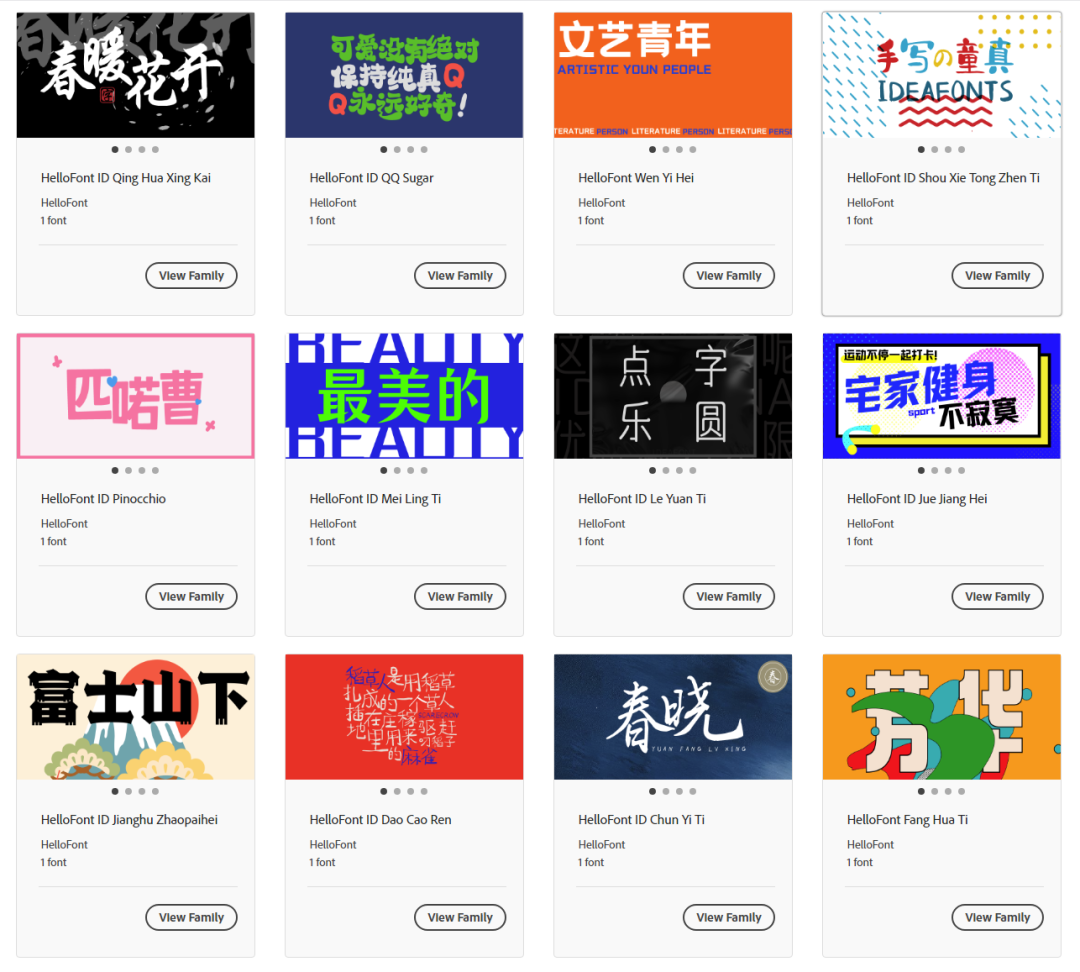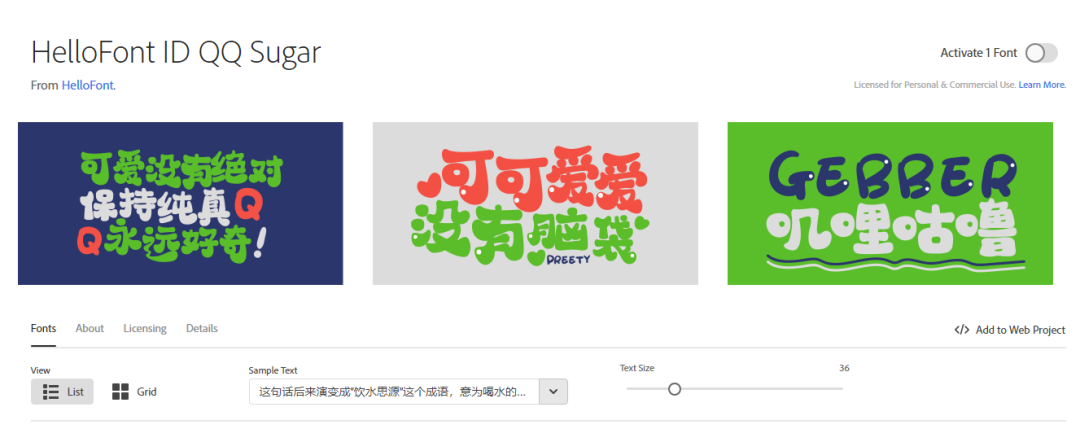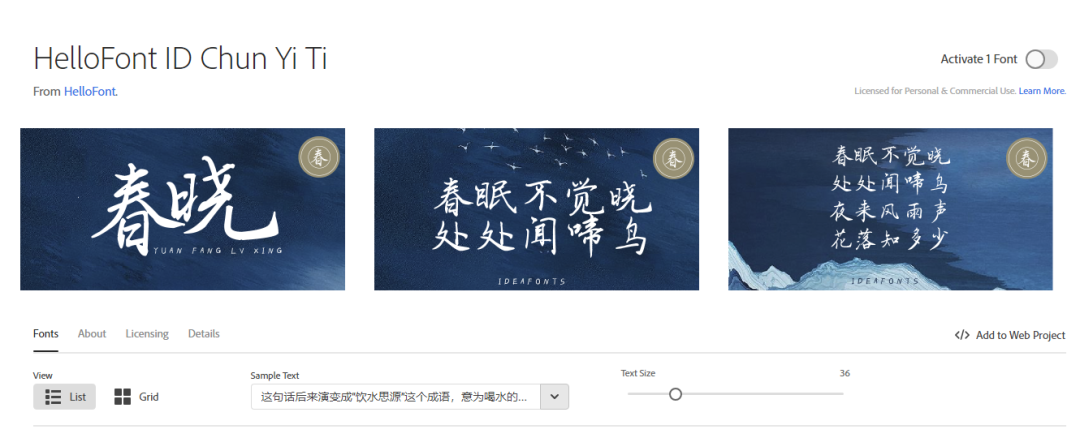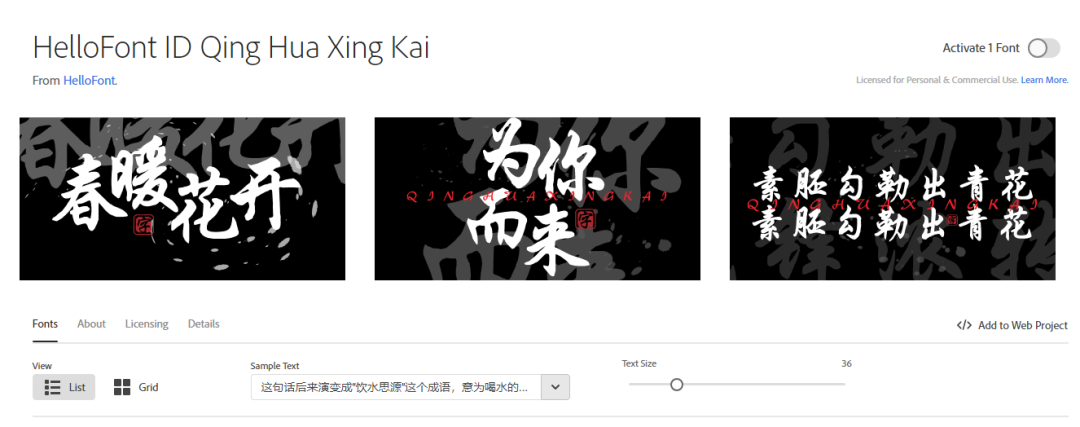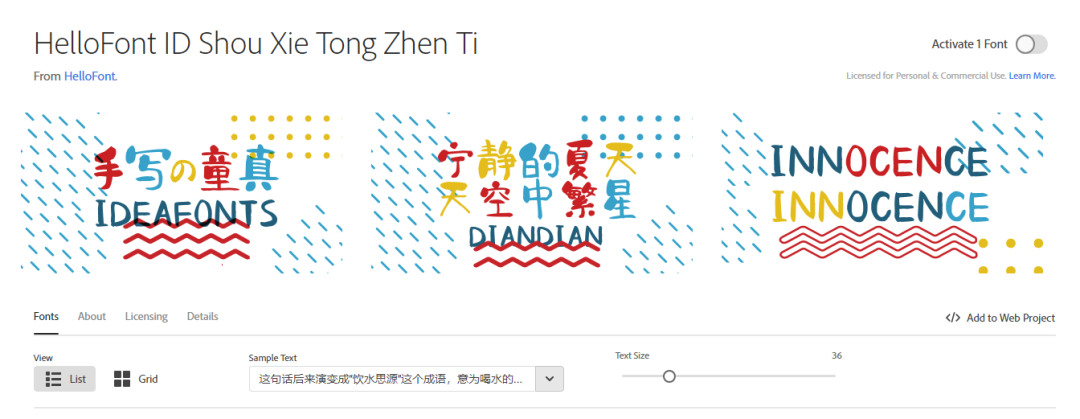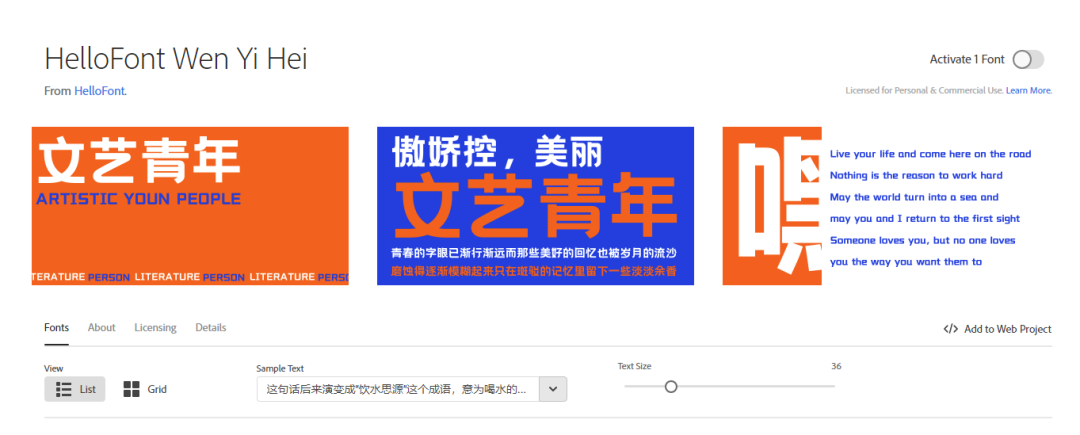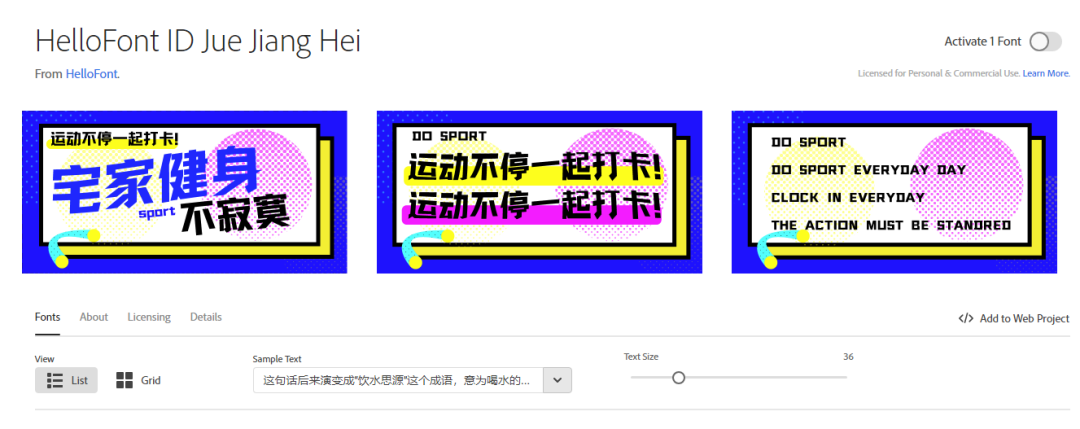
你已经是个成熟的Adobe了,应该有字由的字体!
最近字由合作的平台一个比一个大,一个比一个知名,今天终于轮到我们日思夜想,每天都会见到的Adobe爸爸了~
比如我们都很熟悉的字由芳华体、字由文艺黑。
还有经典的点字青花行楷、点字春意体。
可爱有趣的点字QQ糖、点字手写童真体、点字匹喏曹、点字稻草人。
优雅时尚的点字乐圆体、点字美玲体。
充满力量的点字倔强黑、点字江户招牌黑。